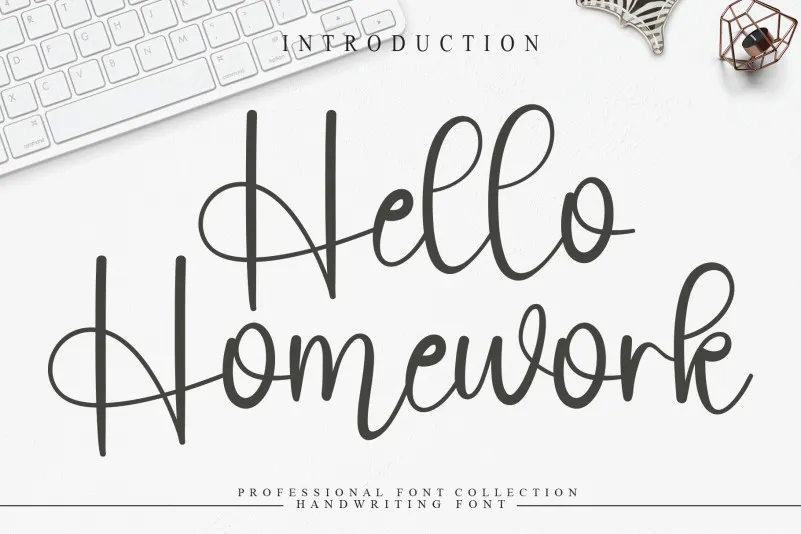
Aqui está uma breve descrição para a página de download da fonte ‘Hello Homework Script Font’: Se você busca algo que dê vida à sua produção criativa e faça dela um momento memorable, o Hello Homework Script Font é o item perfeito. Criado pelo designer creativeletter, este estilo handwritten oferece os detalhes finos que você precisa para alcançar um resultado impecável. Com traços delicados e uma personalidade única, esta fonte não apenas enriquecerá seu trabalho, mas também o fará destacar entre a multidão de designers digitais. Seu estilo casual e descontraído é ideal tanto para aqueles que querem dar um toque especial em mensagens pessoais ou cartões de visita, quanto para projetos mais formais. Com sua versatilidade, você pode encontrar o equilíbrio perfeito entre a simplicidade da escrita semifinal e a personalidade única do seu design. Então, se está procurando por algo que seja um pouco de tudo: elegante mas não formal, sofisticado mas não distinto — o Hello Homework Script Font é definitivamente o item para você.